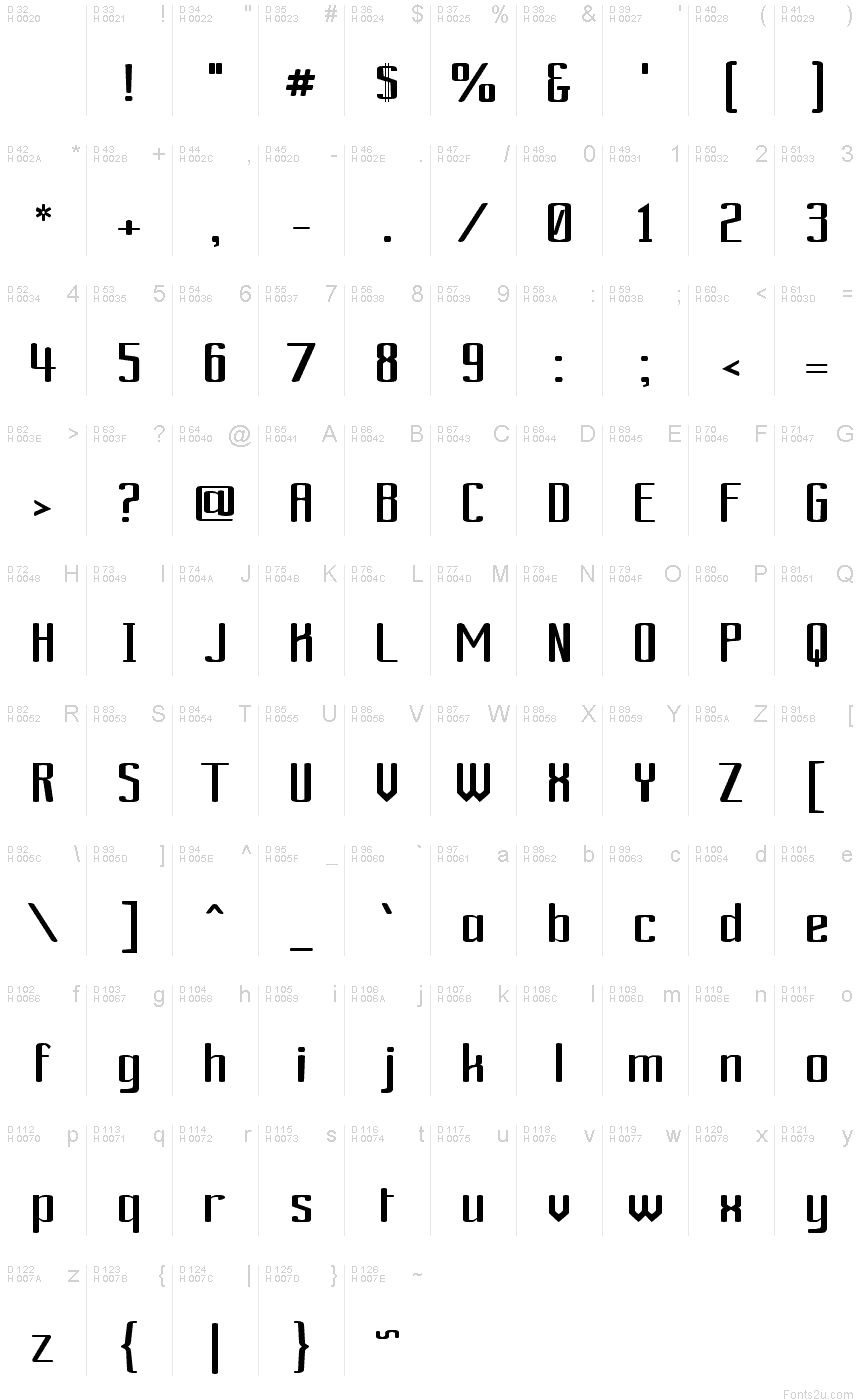
Ardour di Graham Meade è un font display moderno e gratuito che unisce forme tozze e verticali a spazi interni arrotondati, simili a pillole. Le sue colonne alte e curve e gli spazi interni scavati creano un ritmo audace, quasi architettonico, che appare al tempo stesso retro e futuristico. Le lettere sembrano modellate anziché disegnate, con una lucentezza morbida e plastica che rende le parole solide e memorabili a colpo d'occhio.
Con Ardour, ottieni una voce forte e coesa che attira l'attenzione senza risultare aggressiva. Questo font gratuito è perfetto per poster, logotipi, copertine di album, branding tecnologico o gaming, packaging e grafiche d'impatto per i social media. Usa Ardour in grande formato e lascialo respirare, poi abbinalo a un semplice font sans serif geometrico per i testi di supporto, così da far risaltare davvero la sua personalità scultorea.